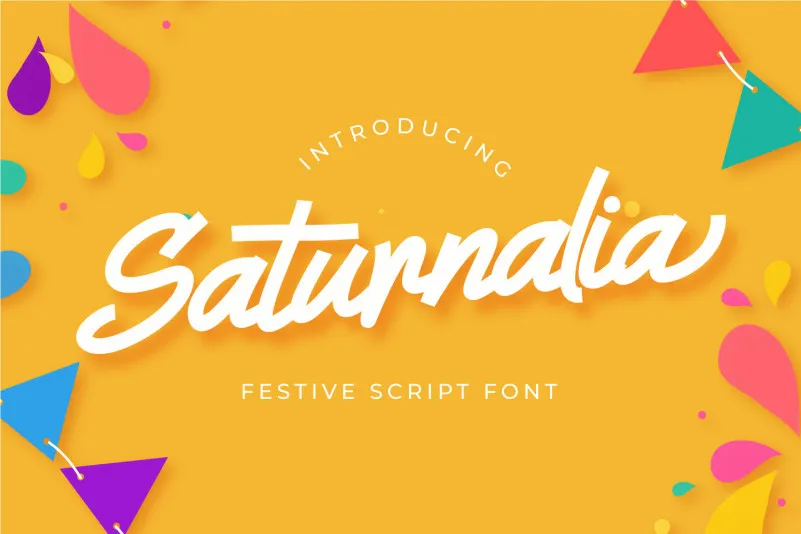
Saturnalia Font – Download Grátis
A fonte ‘Saturnalia Font’ é uma elegante e eterna fonte de escrita a mão. Ela surge perfeitamente para criar logomarcas, identidades visuais e frases intrigantes que chamem atenção. Cada letra exibe um toque único e encantador, potencializando sua habilidade em tornar qualquer design viver mais do que existir. Desenvolvida pelo designer Heloyud, esta fonte é uma escolha perfeita para aqueles criadores de conteúdo que buscam aprimorar suas criações. Seja você um designer gráfico ou um artista visual, ‘Saturnalia Font’ pode ser o toque final necessário em seu trabalho.
Designer: Heloyud